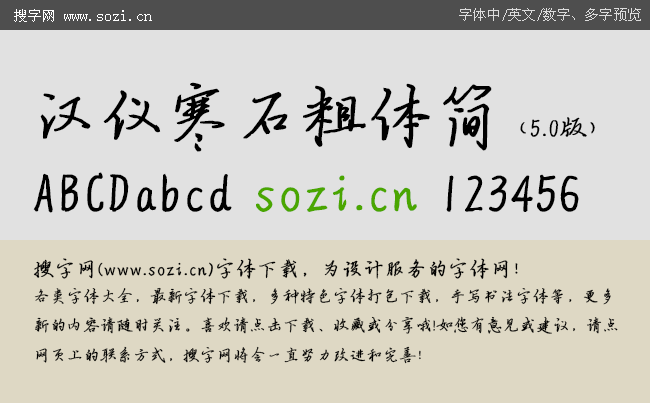
漢儀寒石粗體簡5.0版
漢儀寒石粗體簡5.0版是搜字網(wǎng)給大家提供一款漢儀字體公司出品的書法中文字體下載,該款字體屬于手寫體中的硬筆書法,是介于楷書、草書之間的一種書體,可謂之為行書。在書寫時,不乏楷書的端莊、穩(wěn)重,同時又不失草書的飄逸、灑脫。相信你一定會喜歡在自己作品中用到這款中文字體!歡迎下載!